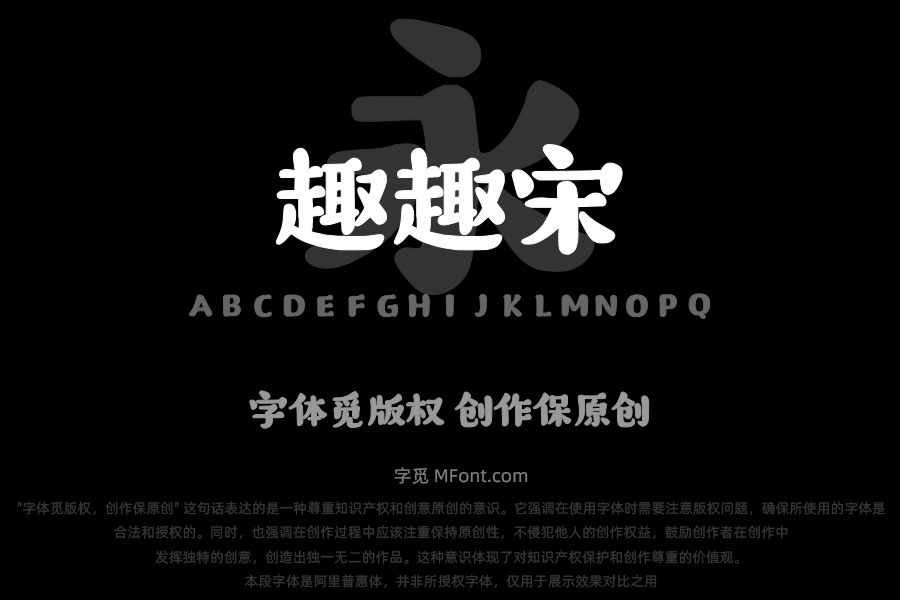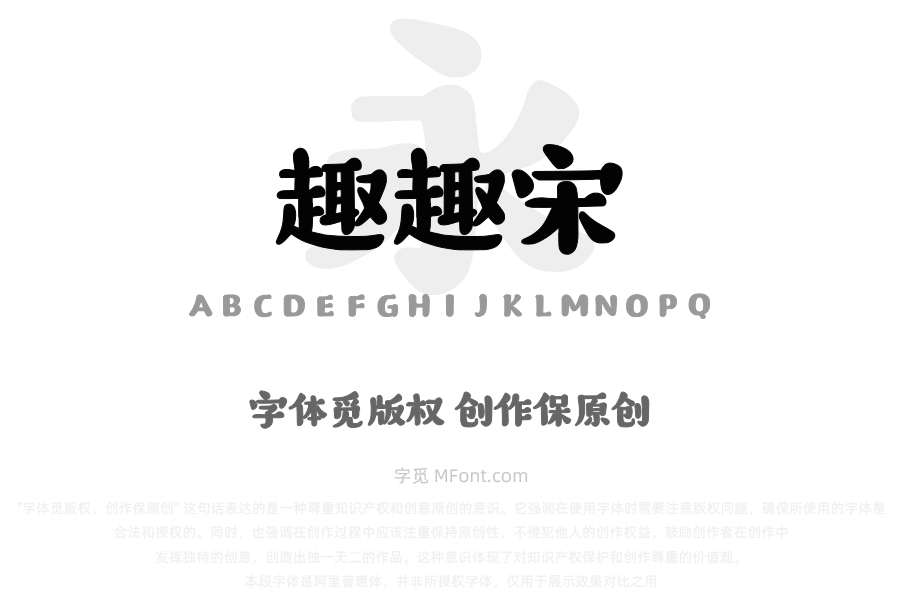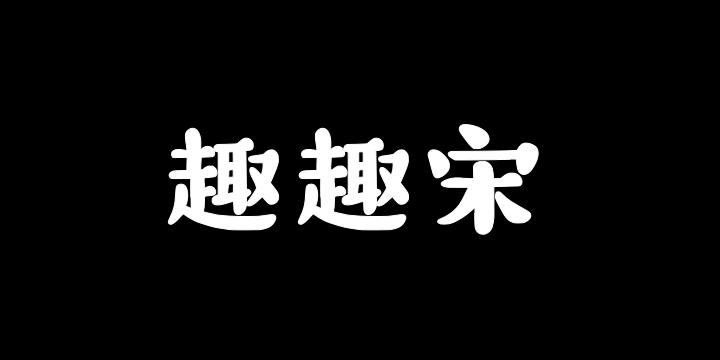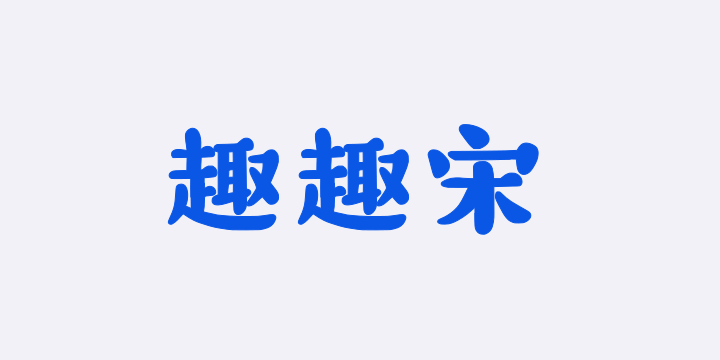
关于字潮趣趣宋字体字库信息
字体全名: 字潮趣趣宋
铸字厂: 字潮字库
设计师: 丁道华
字体简介: 字潮趣趣宋脱胎于经典宋体,却大胆跳脱传统框架的束缚,在保持宋体原有骨架与端庄气质的基础上,巧妙融入了生动活泼的笔触与趣味性表达。其笔画形态富于变化,韵律感十足,仿佛每一个字都在纸面上轻盈起舞,既传承了宋体结构的雅正底蕴,又展现出自由灵动的现代气息。